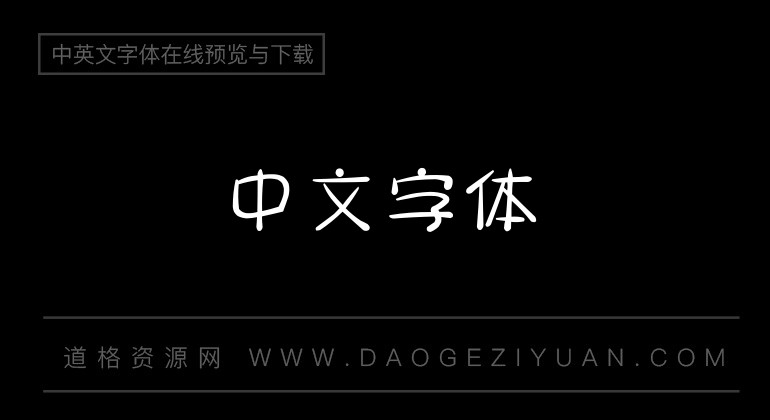
龙顺体
? 龙顺体(Longshun)是一款由英国设计师罗伯特·萨维尔(Robert Savage)创作的简约楷书字体,主要用于英文文本排版,具有良好的可读性和清晰的视觉效果。字体细节精致,笔画柔和,字形节奏顺畅,可以有效地提升文本的可读性和可视性。
龙顺体是一款非常不错的手写艺术字体,具有很好的视觉感,适合于文化类的宣传设计、商业类品牌的广告和产品包装设计以及个性化文字排版等较多场景。